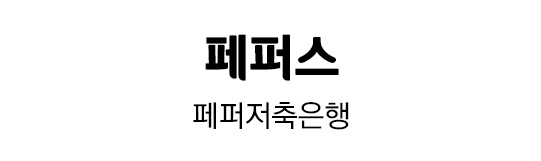
페퍼저축은행 로고의 특징을 담은 제목용 서체
기존 로고의 특징을 한글과 영문에 접목하여 전체적인 외곽 굴림과 세로 획의 둥그런 깎임, 그리고 빗침에 라운드 처리가 된 것이 특징인 서체입니다.
페퍼저축은행 전용서체 '페퍼스'
한글 11,172자 / 영문 94자 / 약물 986자